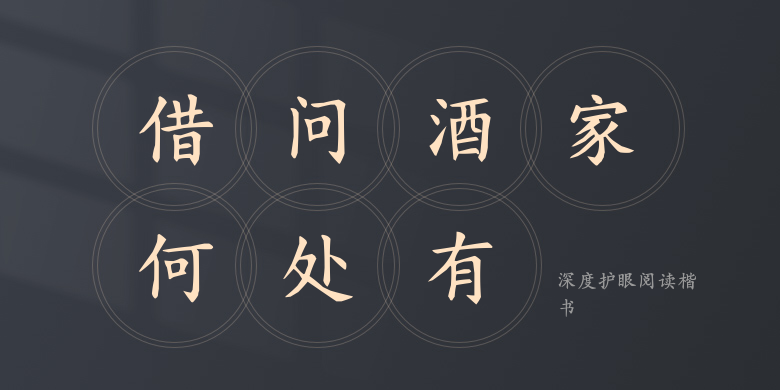
深度护眼阅读楷书
深度护眼阅读楷书,这款字体结构工整、笔画清晰,兼顾美观与易读性,适用于标题、正文、海报、包装、LOGO 等多种场景。字形优雅稳定,风格百搭耐看,适配日常排版与创意设计,让文字呈现更舒适、更具质感。深度护眼阅读楷书一笔一画,皆是细节,以均衡的比例、流畅的线条打造舒适视觉体验,字形端正大气,风格简约现代。无论是商业设计、品牌宣传还是日常排版,都能轻松驾驭,让文字更有格调与力量。深度护眼阅读楷书字体下载。